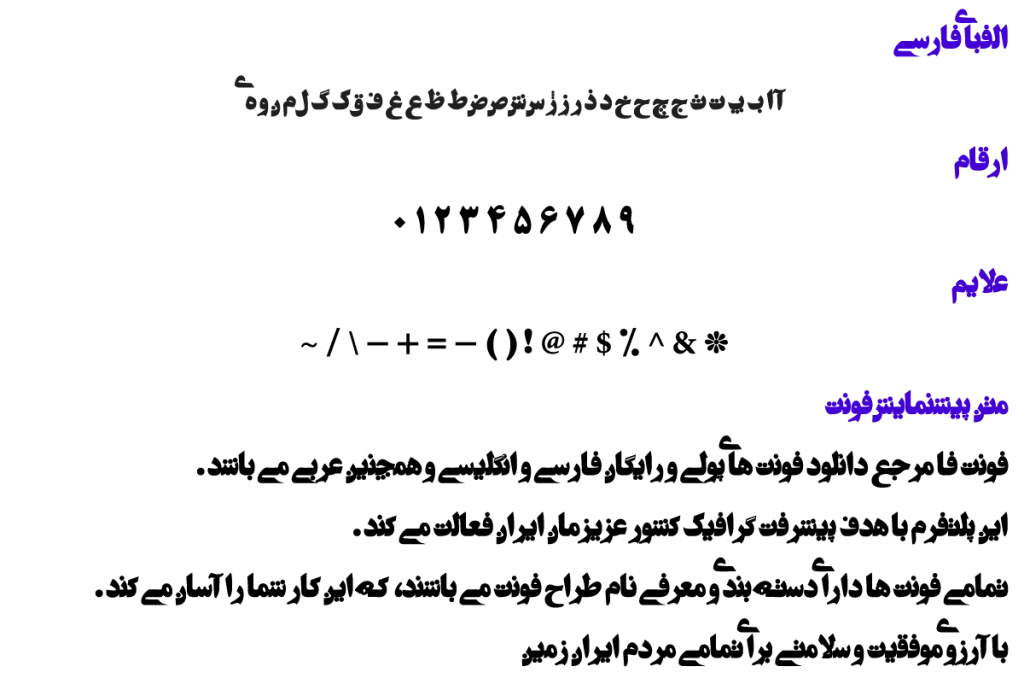
فونت فارسی تیتراژ – A Titraj
مجموعه فونت: فونت سری پرشین
طراح فونت: امیر حسین صدقی نوع فونت: فونت گرافیکی
پیشنمایش فونت تیتراژ
توضیحات و معرفی فونت تیتراژ
فونت فارسی تیتراژ نسخه 1 و 2 ( A Titraj ) از مجموعه فونت های سری پرشین می باشد، و نیز نوع فونت گرافیکی می باشد.
فونت خوشگل مربوط توسط امیر حسین صدقی در سال 1390 طراحی و ساخته شده است.
و نیز فونت A Titraj در یک وزن پر رنگ است.
- A Titraj Bold
شعر فارسی با حال و هوای وطن، نوشته شده با این تایپ فیس، در عکس زیر قابل مشاهده است.